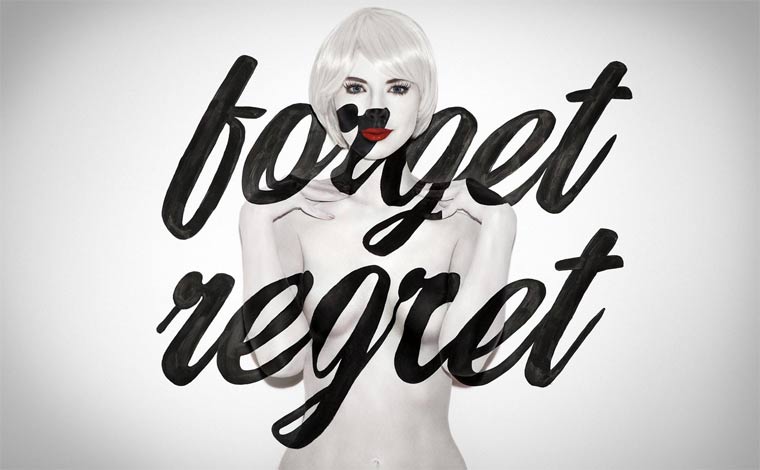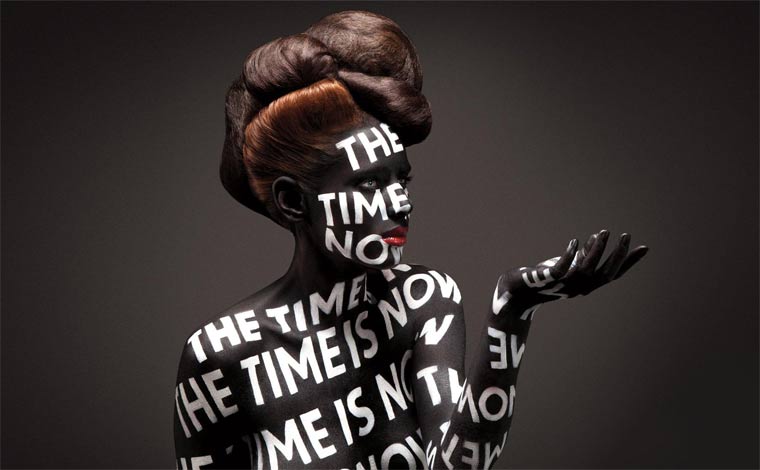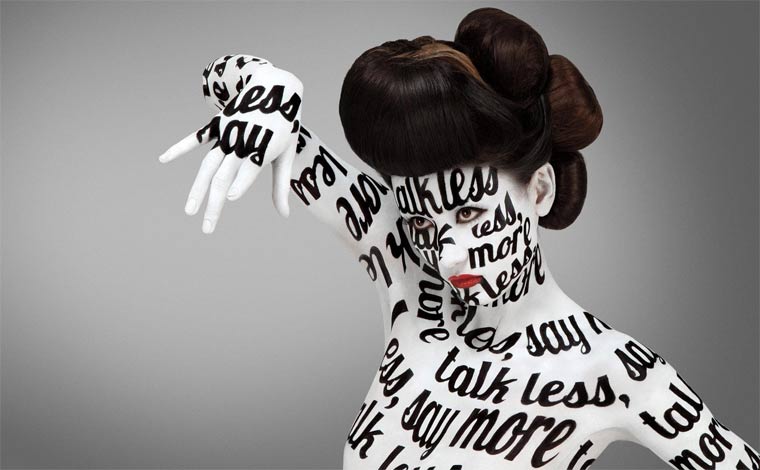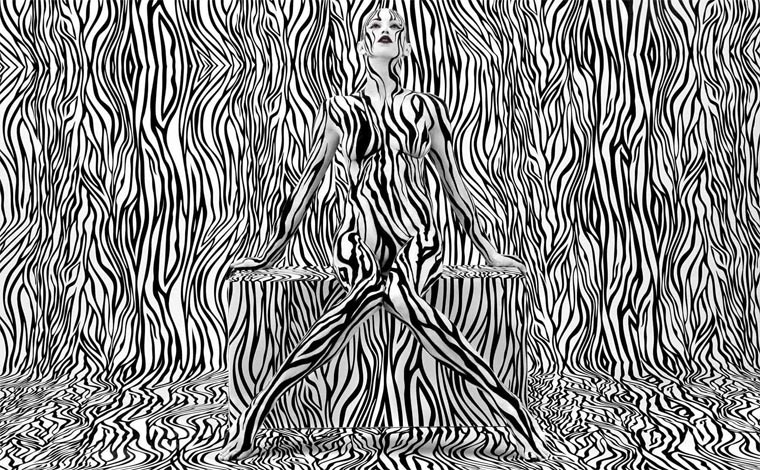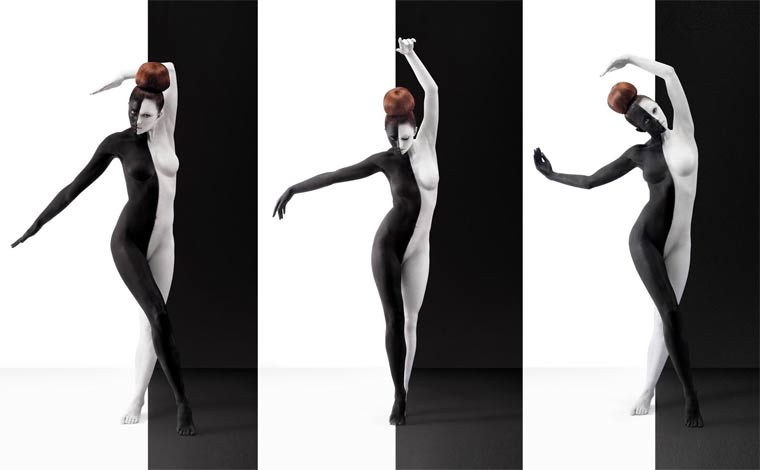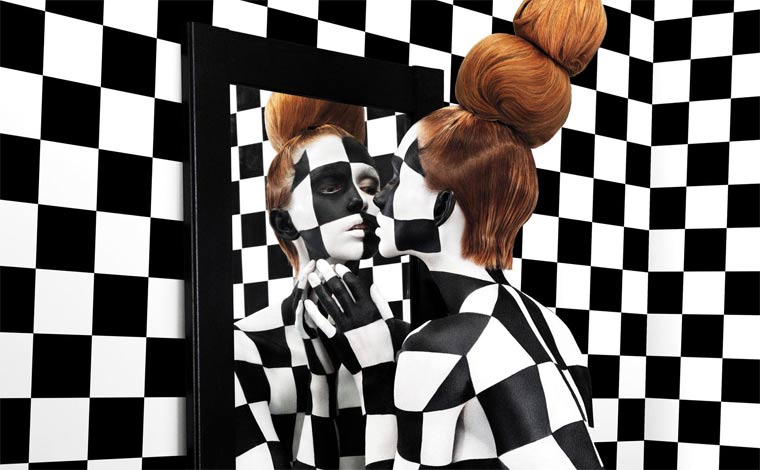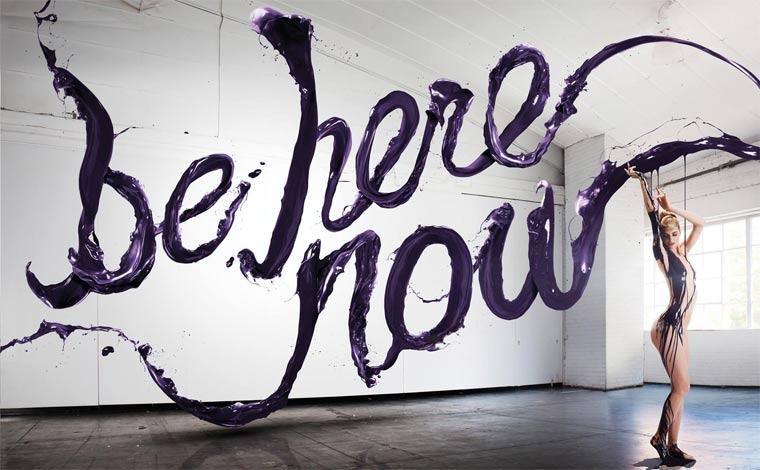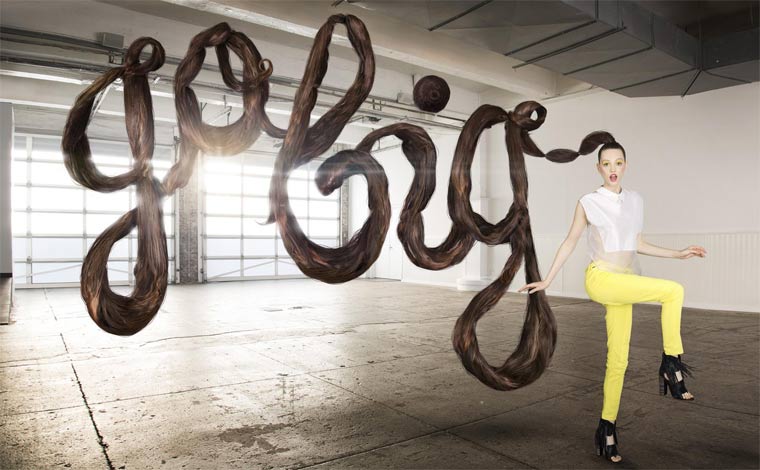
Tolle Typografie-Bodypaintings von Aizone aizone_01
Hinter der Kollaboration Aizone stecken Stefan Sagmeister und Jessica Walsh. Neben vielem Anderen haben sie auch einige Bodypaintings verwirklicht, bei denen Sätze, Formen oder Buchstaben den Weg auf Model und/oder Hintergrund geschafft haben. Teils sehr tolle Arbeiten, die sich nicht zuletzt aufgrund dieses skurrilen Mixes sehen lassen können.
Tolle Typografie-Bodypaintings von Aizone aizone_02
Tolle Typografie-Bodypaintings von Aizone aizone_03
Tolle Typografie-Bodypaintings von Aizone aizone_04
Tolle Typografie-Bodypaintings von Aizone aizone_05
Tolle Typografie-Bodypaintings von Aizone aizone_06
Tolle Typografie-Bodypaintings von Aizone aizone_07
Tolle Typografie-Bodypaintings von Aizone aizone_08